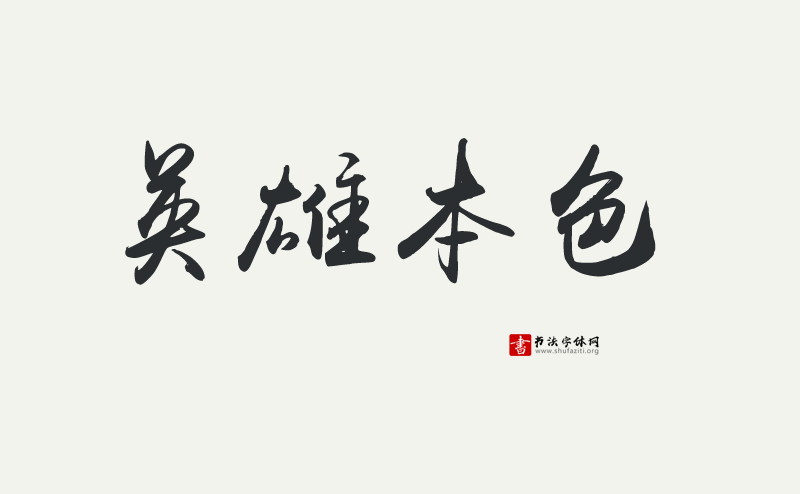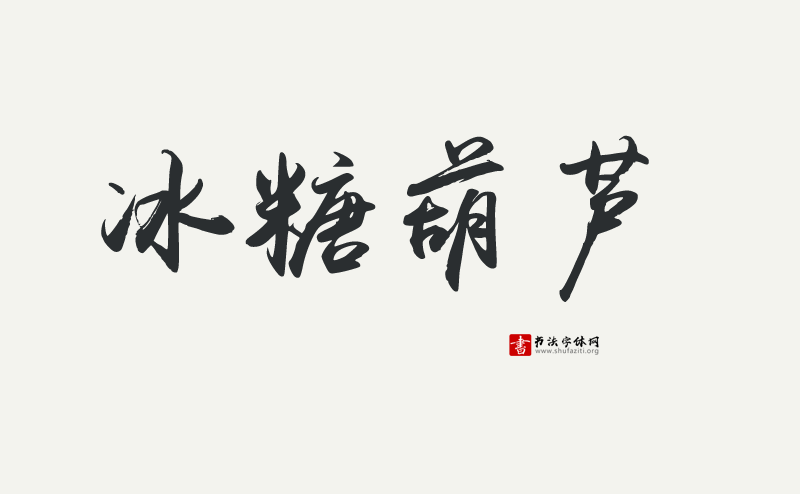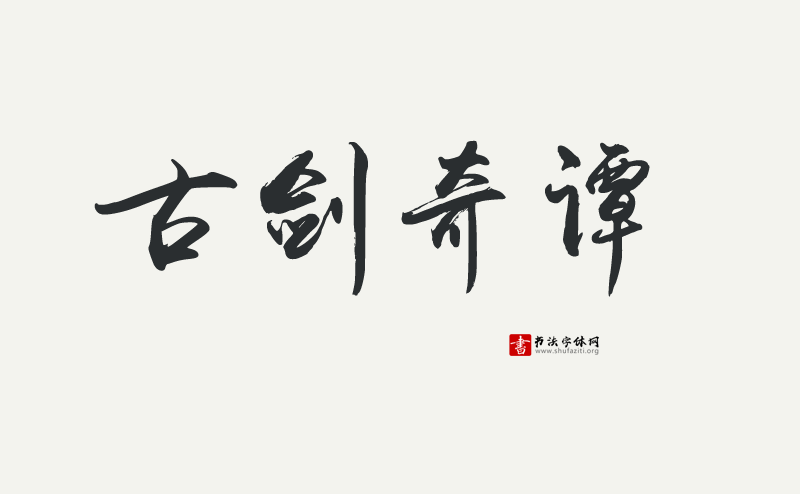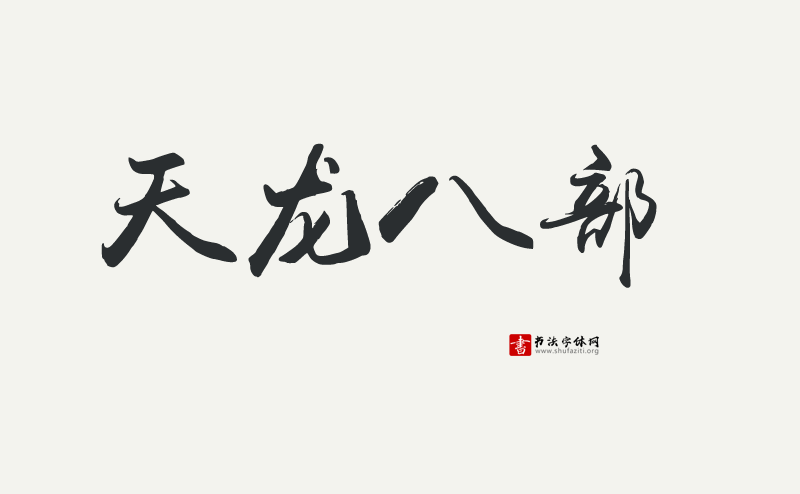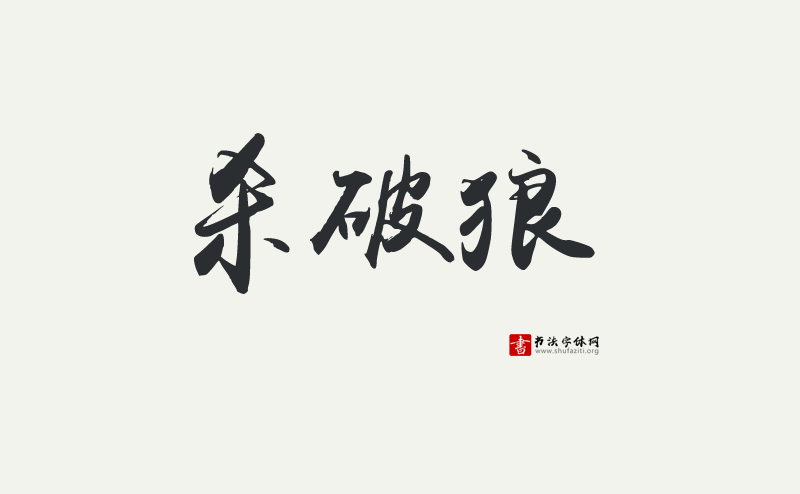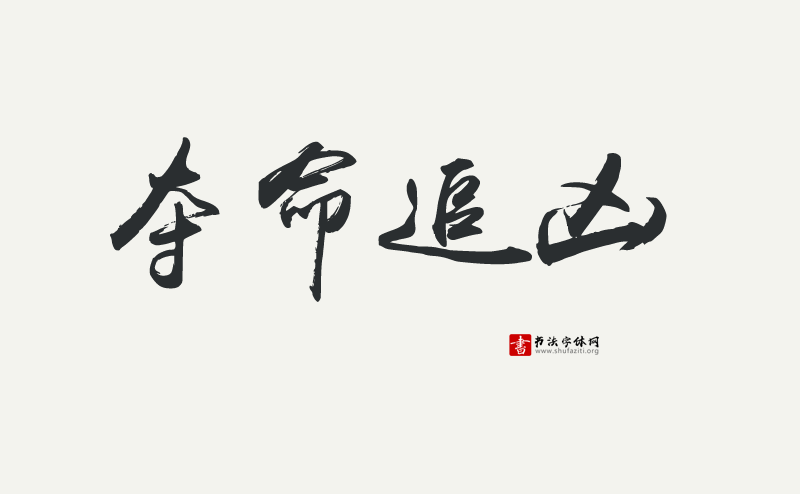
禹卫书法行书简体
《禹卫字体》系列是国内知名文字创意人禹卫先生所开发制作,自2012年以来,相继开发制作出《禹卫硬笔常规体》、《禹卫书法行书体》、《禹卫书法隶书体》,这些字体均是GB_2312字库,均包含了常用字和生僻字,其中后两种字体是分为简、繁两套字体,广泛适用于微软OFFICE的各种软件、QQ、MSN等常用聊天工具、PHOTOSHOP等主流绘图软件。
| 创作时间 | 字体名称 | 作者 | 文字类别 |
| 2012年7月 | 禹卫硬笔常规体 | 禹卫 | 简体 |
| 2013年11月 | 禹卫书法行书简体 | 禹卫 | 简体 |
| 2014年3月 | 禹卫书法行书繁体 | 禹卫 | 繁体 |
| 2014年6月 | 禹卫书法隶书简体 | 禹卫 | 简体 |
| 2014年8月 | 禹卫书法隶书繁体 | 禹卫 | 繁体 |
禹卫,江苏扬州人,国内知名文字创意人、禹卫字体创始人、中国书画艺术研究院扬州分院副院长,自幼习书,毛笔硬笔兼修,习书二十多年来不断在文字上创新,他将的座右铭是:让文字散发光芒,将线条赋予生命“,并一直勤于笔耕,寒暑不断,在电脑字体几乎垄断了用户界面的情况下,书法字体的出现让用户眼前一亮,而书法字体的线条多样性也丰富了各行业设计师们的选择,《禹卫字体》系列正是在填补了这方面的空缺。